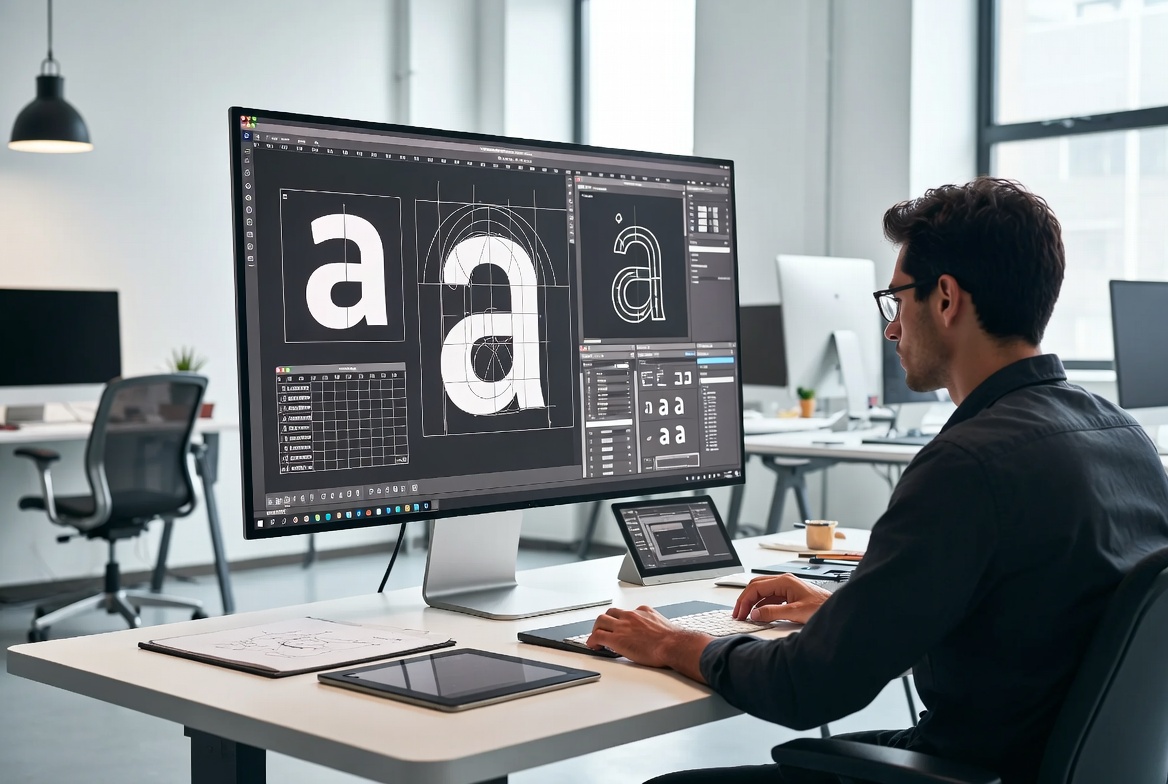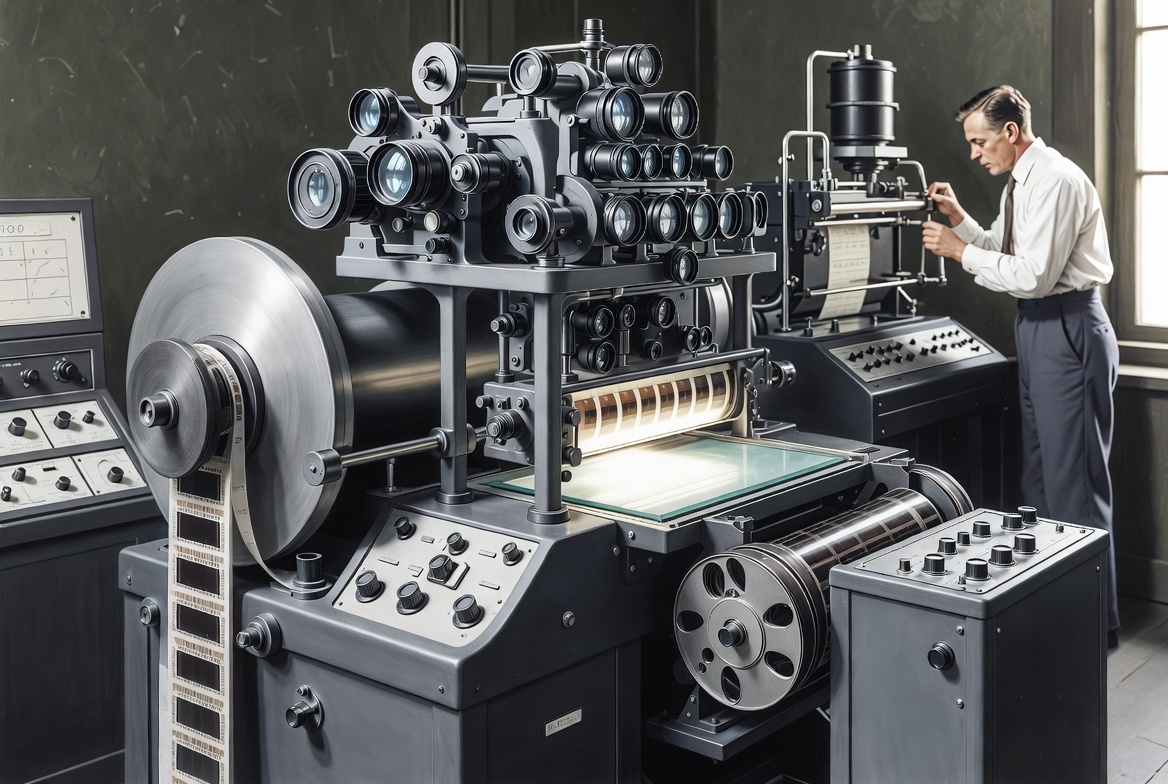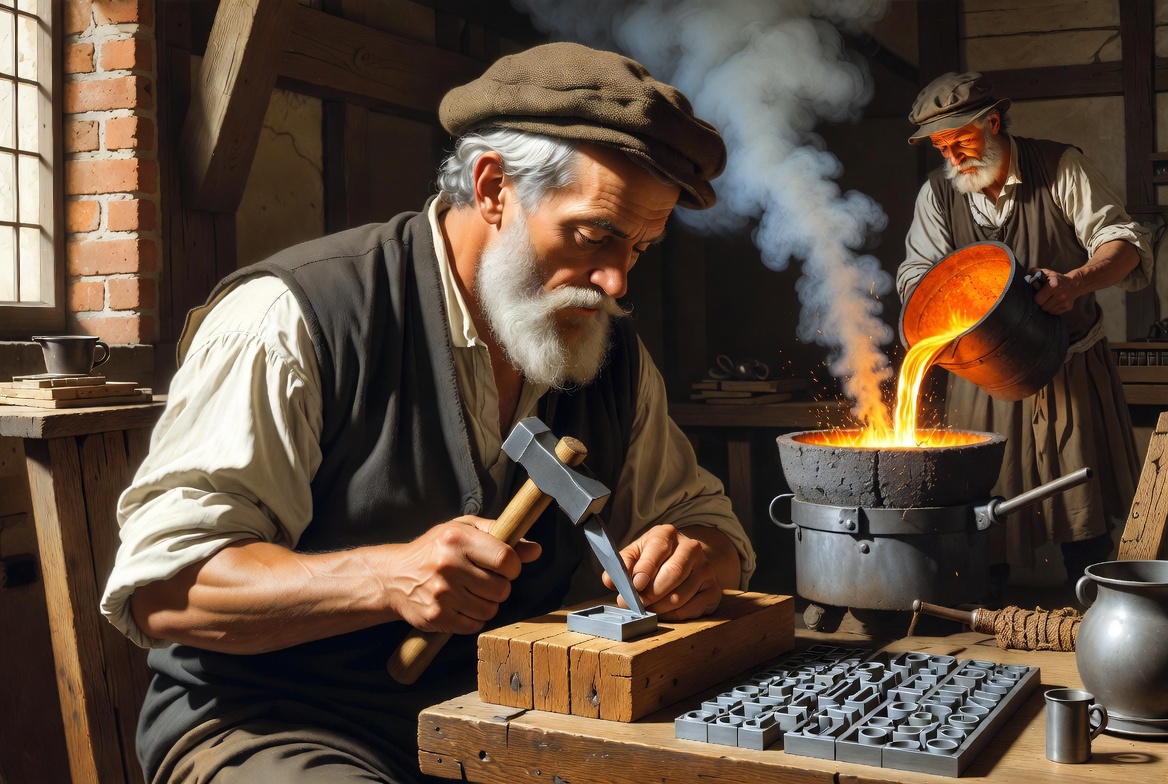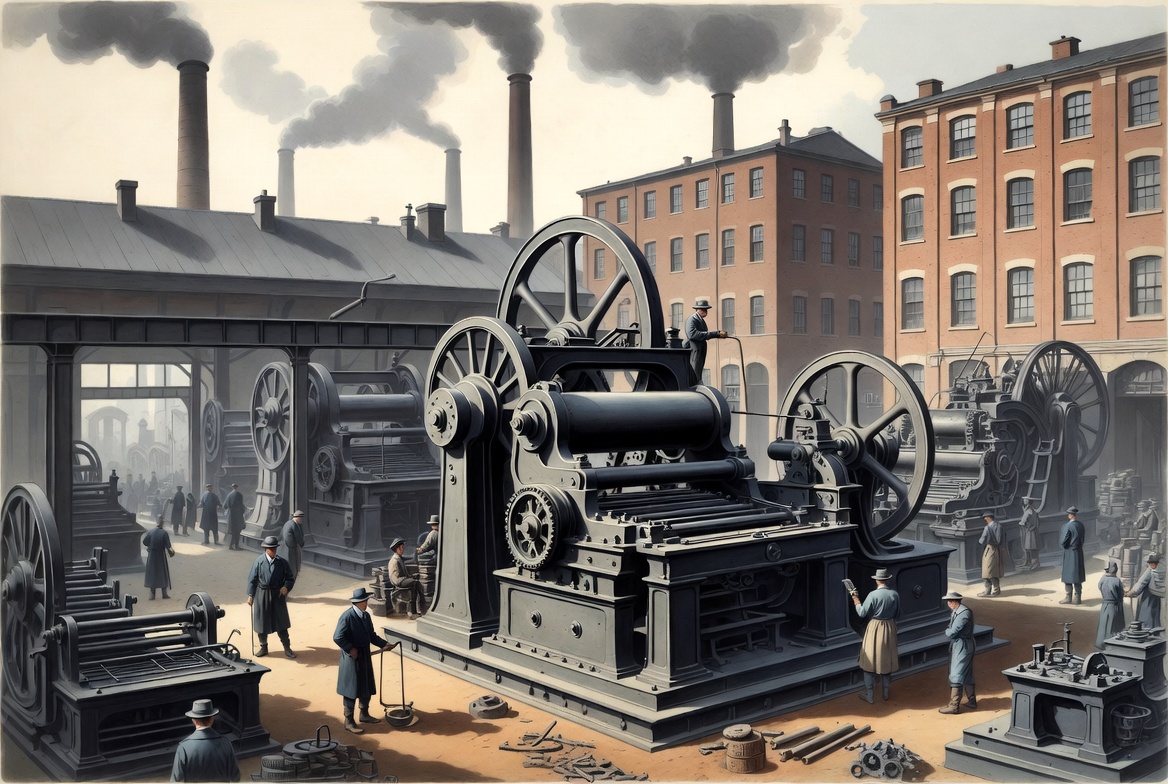
Schriftenhersteller – Teil 1: Einführung
Was ist ein Schriftenhersteller? Ein Überblick über die Entwicklung von den klassischen Schriftgießereien bis zu den digitalen Type Foundries von heute.
Nachdem wir in der vorherigen Serie die lange Geschichte der Schrift von den ersten Keilschrifttafeln bis zur digitalen Typografie nachgezeichnet haben, richten wir den Blick nun auf die Akteure, die Schriften entwerfen, herstellen und verbreiten. Denn ohne Schriftenhersteller – früher Schriftgießereien, heute Type Foundries – wäre die schriftliche Kommunikation in der Form, wie wir sie kennen, nicht möglich.
Was ist ein Schriftenhersteller?
Ein Schriftenhersteller (englisch: Type Foundry) ist ein Unternehmen oder eine Organisation, das Schriften entwirft, produziert und lizenziert. Früher bedeutete das vor allem das Schneiden von Stempeln und das Gießen von Bleilettern. Heute umfasst die Tätigkeit vor allem den Entwurf digitaler Schriftarten, deren technische Aufbereitung und den Vertrieb über Lizenzen.
Schriftenhersteller stehen damit an einer zentralen Stelle der visuellen Kommunikation: Sie liefern das Werkzeug, mit dem Texte gestaltet, gelesen und verstanden werden.
Von der Schriftgießerei zur digitalen Foundry
Die Geschichte der Schriftenhersteller lässt sich grob in mehrere Phasen unterteilen:
1. Handwerkliche Anfänge
In der Zeit nach Gutenberg waren Schriftenschneider und Schriftgießer oft eng mit Druckereien verbunden. Das Schneiden von Stempeln (Punzen) und das Gießen von Lettern war hochspezialisiertes Handwerk.
Illustration der handwerklichen Anfänge: Stempelschneiden und Letternguss
2. Industrielle Schriftgießereien
Ab dem 19. Jahrhundert entstanden große Schriftgießereien, die Schriften in großem Maßstab produzierten und international vertrieben. Namen wie Stempel, Bauer, Monotype oder Linotype prägten diese Epoche.
Illustration einer industriellen Schriftgießerei im 19./20. Jahrhundert
3. Fotosatz und Übergang
Mit dem Fotosatz veränderte sich die Produktionsweise erneut. Viele klassische Gießereien passten sich an oder gingen in größeren Unternehmen auf.
Illustration einer Fotosatzanlage
4. Digitale Type Foundries
Seit den 1980er- und 1990er-Jahren dominieren digitale Schriften. Heute gibt es sowohl große Konzerne als auch eine Vielzahl unabhängiger Foundries, die oft nur aus wenigen Personen bestehen.
Illustration einer modernen digitalen Type Foundry
Die heutige Landschaft
Die aktuelle Situation ist geprägt von einer starken Zweiteilung:
- Große Anbieter wie Monotype oder Adobe Fonts verfügen über umfangreiche Schriftbibliotheken und starke Marktpositionen.
- Unabhängige Foundries arbeiten oft spezialisierter, experimenteller oder stärker designorientiert. Viele von ihnen haben in den letzten Jahrzehnten maßgeblich zur Qualität und Vielfalt der verfügbaren Schriften beigetragen.
Daneben gibt es zahlreiche kleinere Studios und Einzelpersonen, die eigene Schriften veröffentlichen.